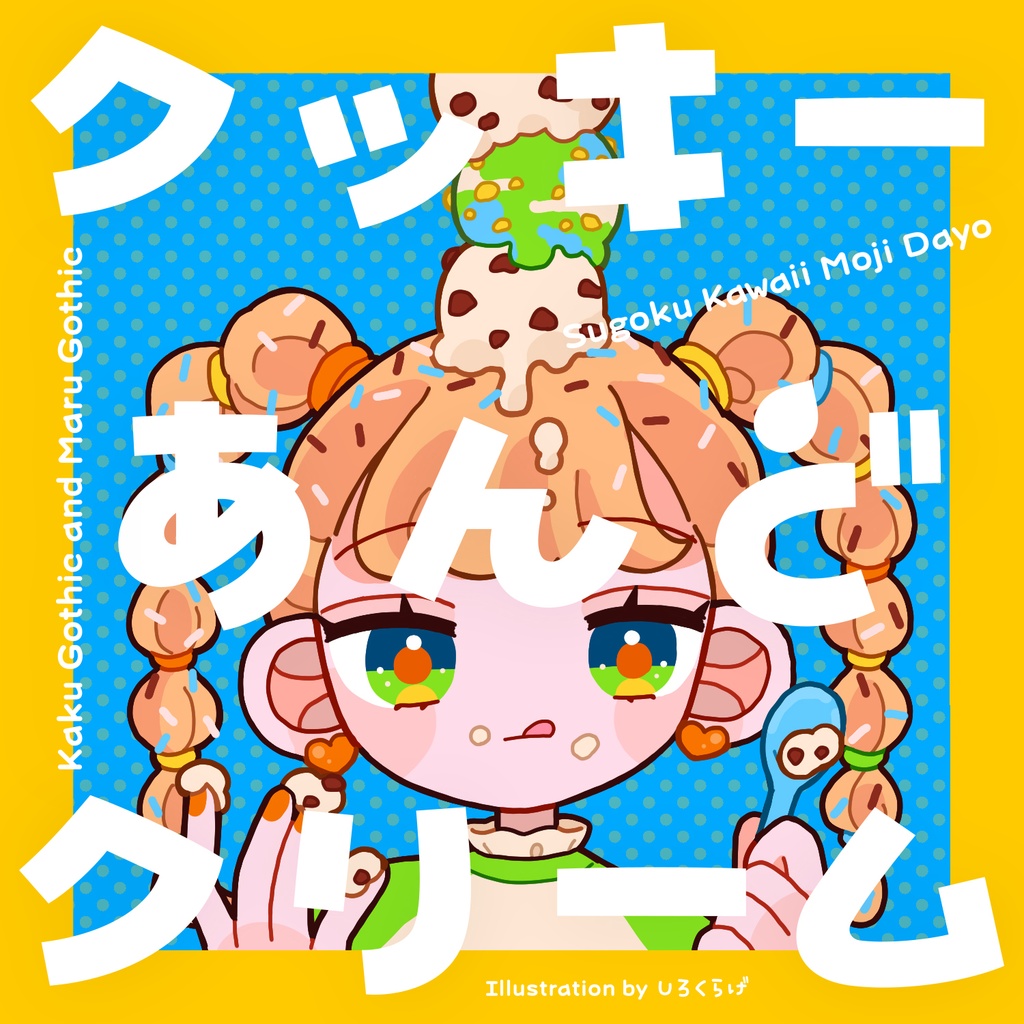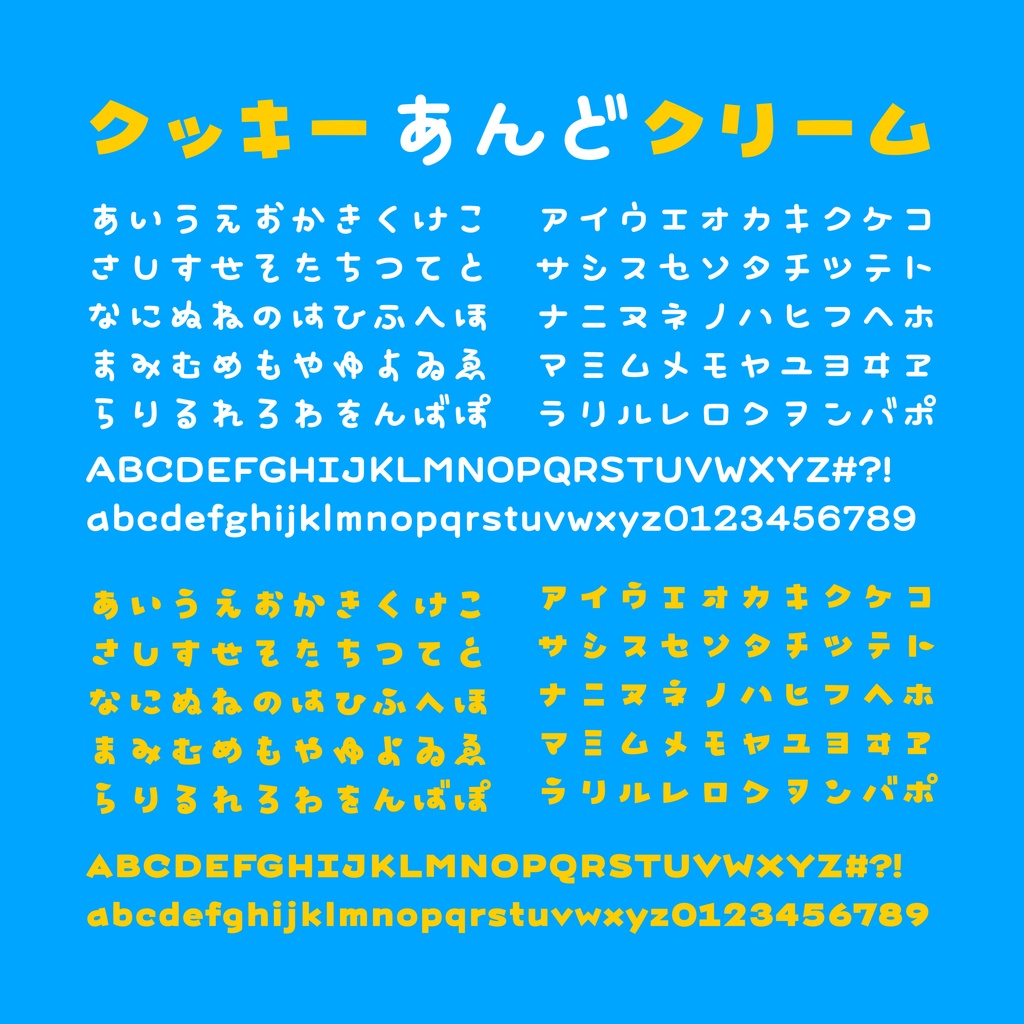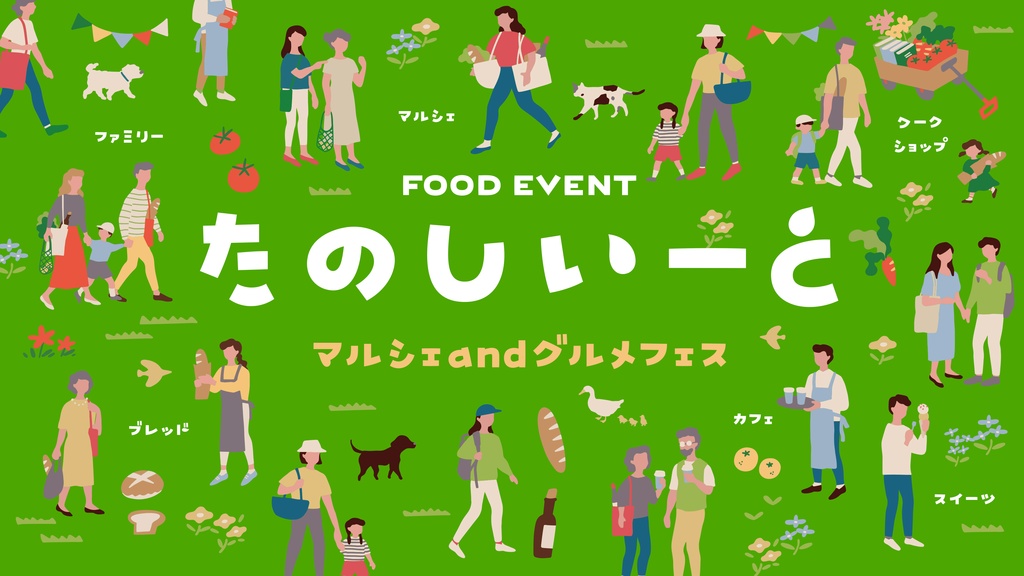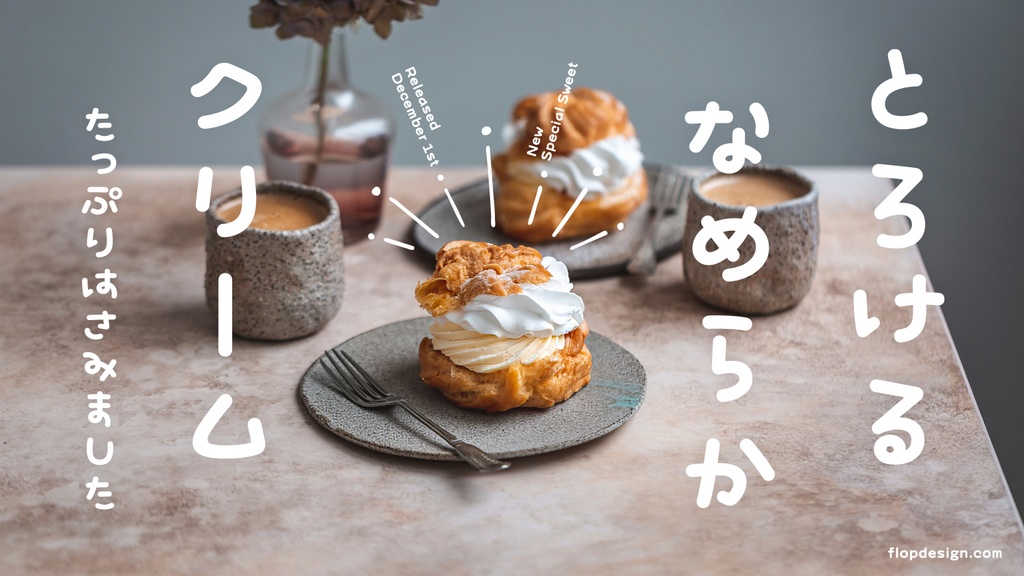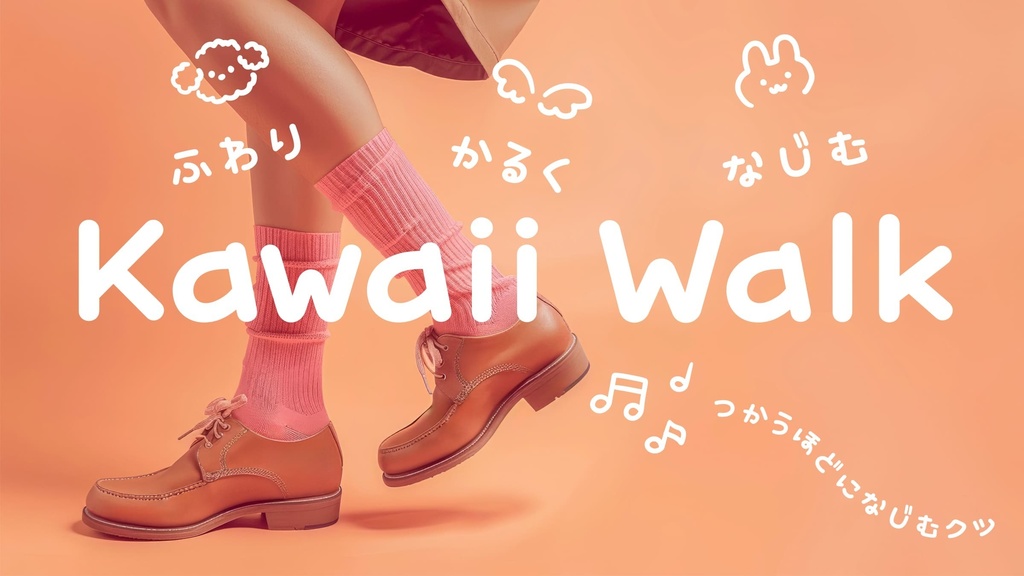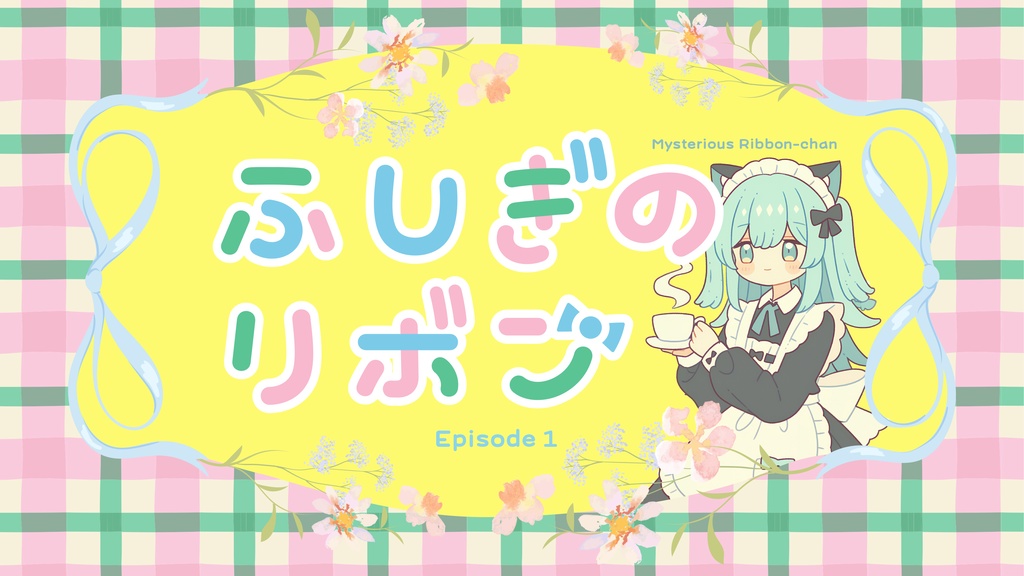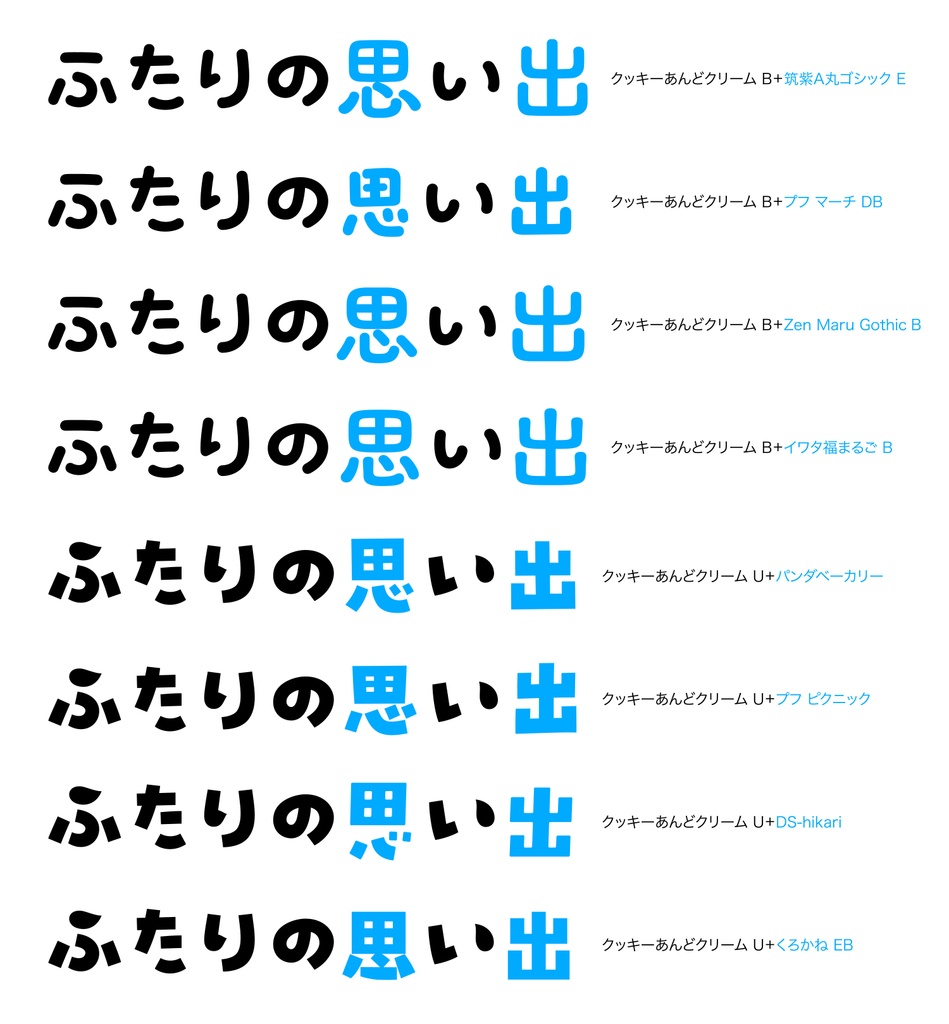
クッキーあんどクリーム フォント
最高にかわいいを目指したフォントです。超かわいい極太角ゴシック体と丸ゴシック体の2つがセットになっています。2000年頃の手描きの平成ギャル文字をベースに令和風に完全リデザインしました。ちょっとチグハグでアンバランスなのが魅力的、大きめの濁点もポイントです。見出しやロゴに使えばパッと目を引くデザインに。 ■動作環境 Mac:システム/OS X対応(10.x)〜最新のOS X Windows:OS/日本語版Windows2000、XP、VISTA、Windows7〜11以降 フォント形式:OpenTypeフォント 1商品(1ライセンス)につき1ユーザー1PCのみがご利用いただけます。人数分をご購入ください。 ■収録文字について 収録文字数427字。アルファベット、ひらがな、カタカナ、約物の一部。 ■安心して使えるロイヤリティフリーの書体 商用・デザイン用途(印刷物・ゲーム・アプリ・映像・動画・ロゴ・同人作品)に使用できる、商用申請の必要のないロイヤリティフリーの書体になります。文字の加工・変形も可能です。ご安心ください。 ■OpenType機能 詰め組み機能 別字形(異体字)※異なる字形を用意しています。